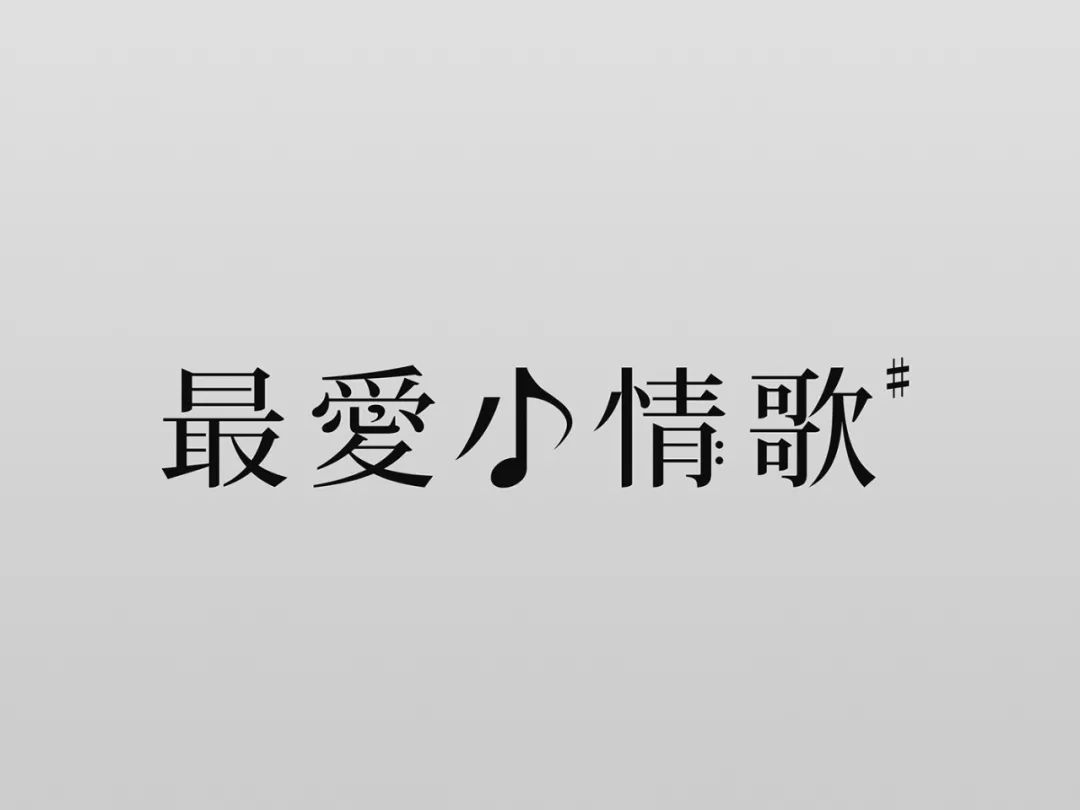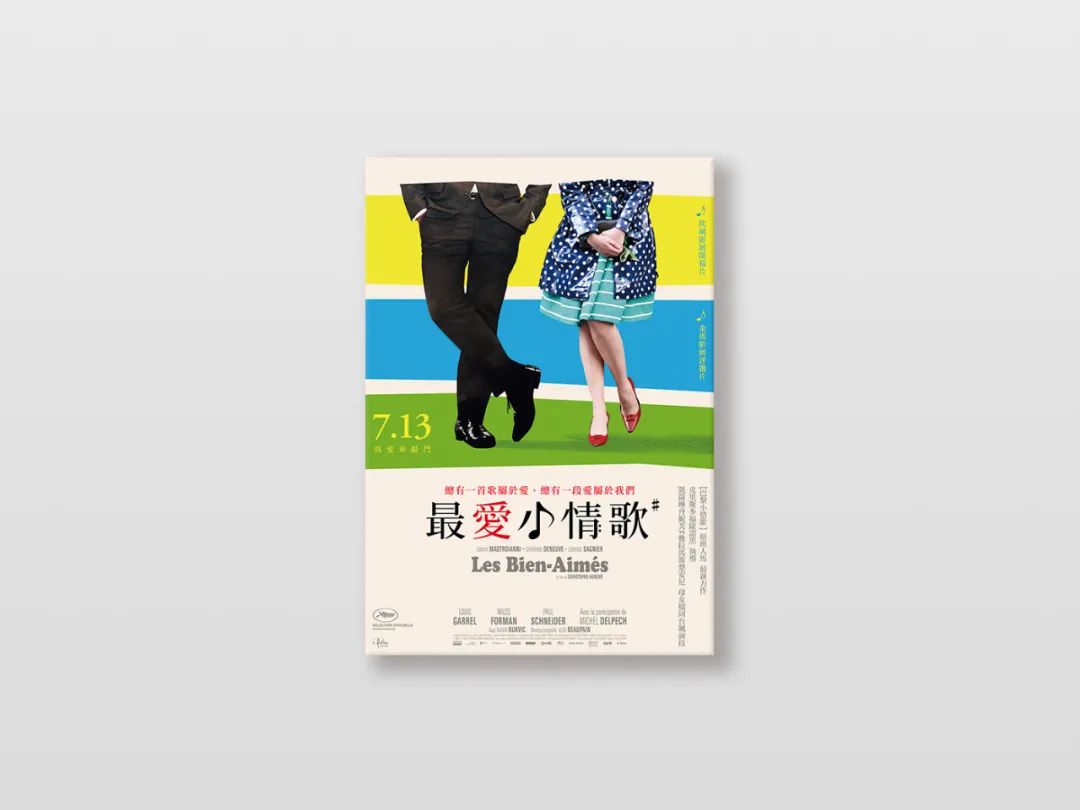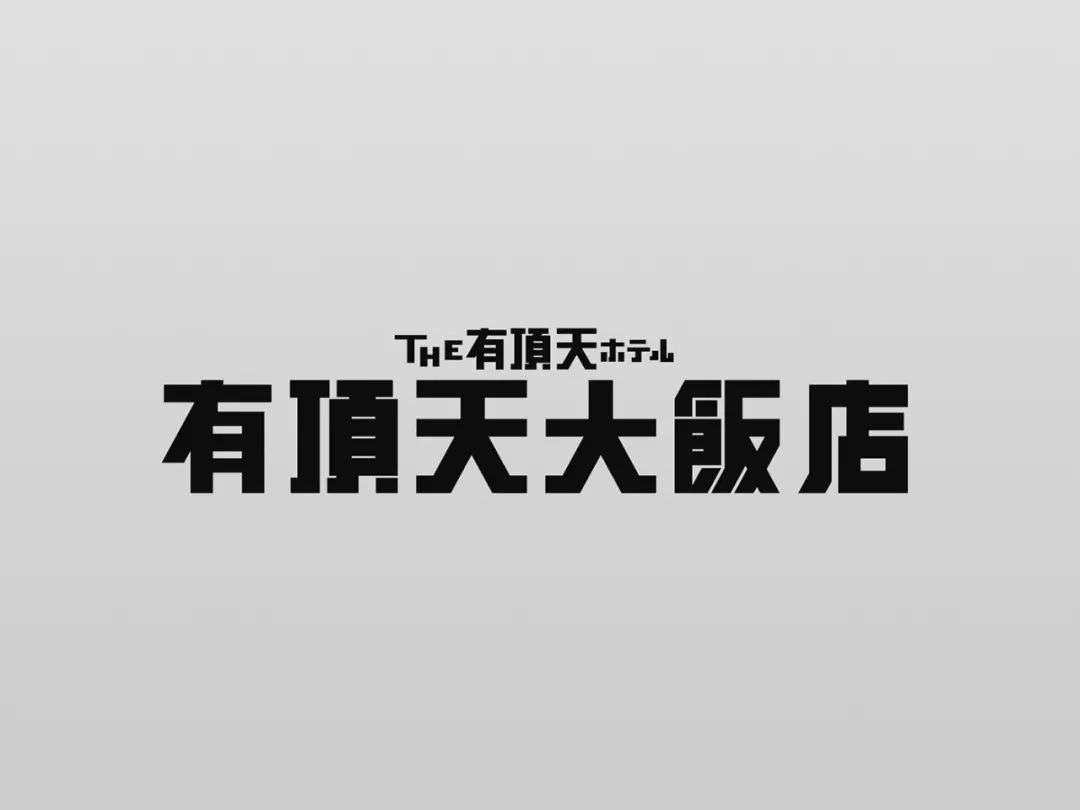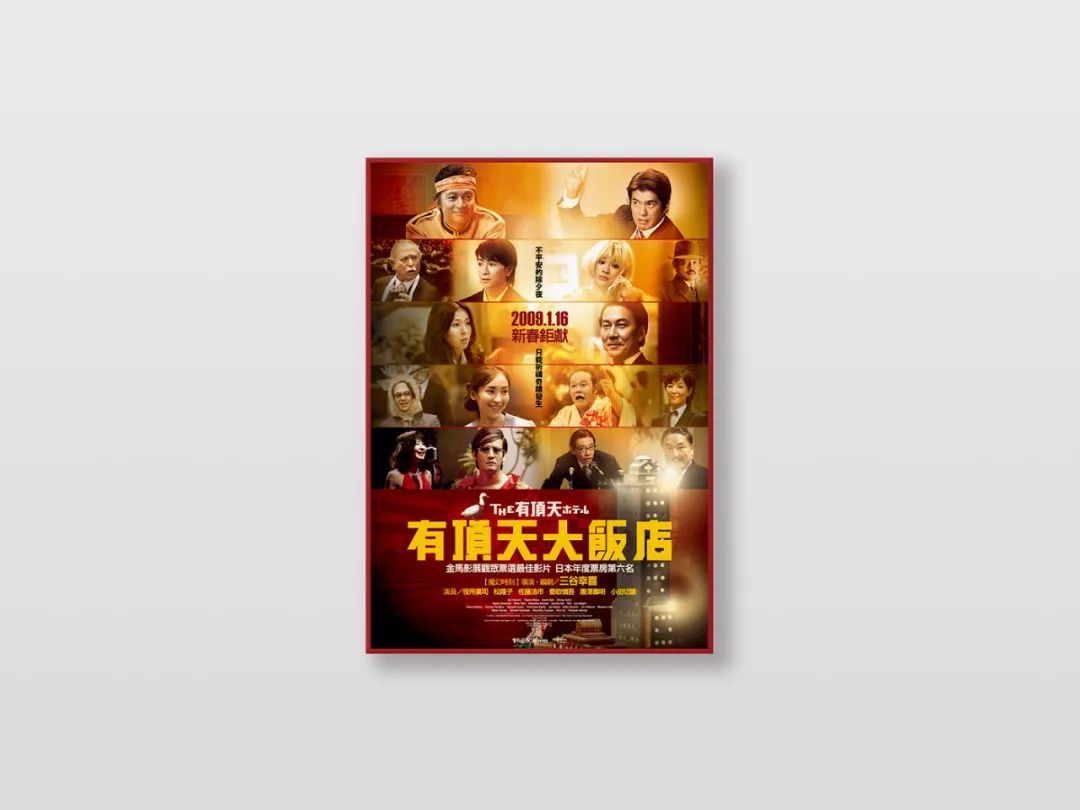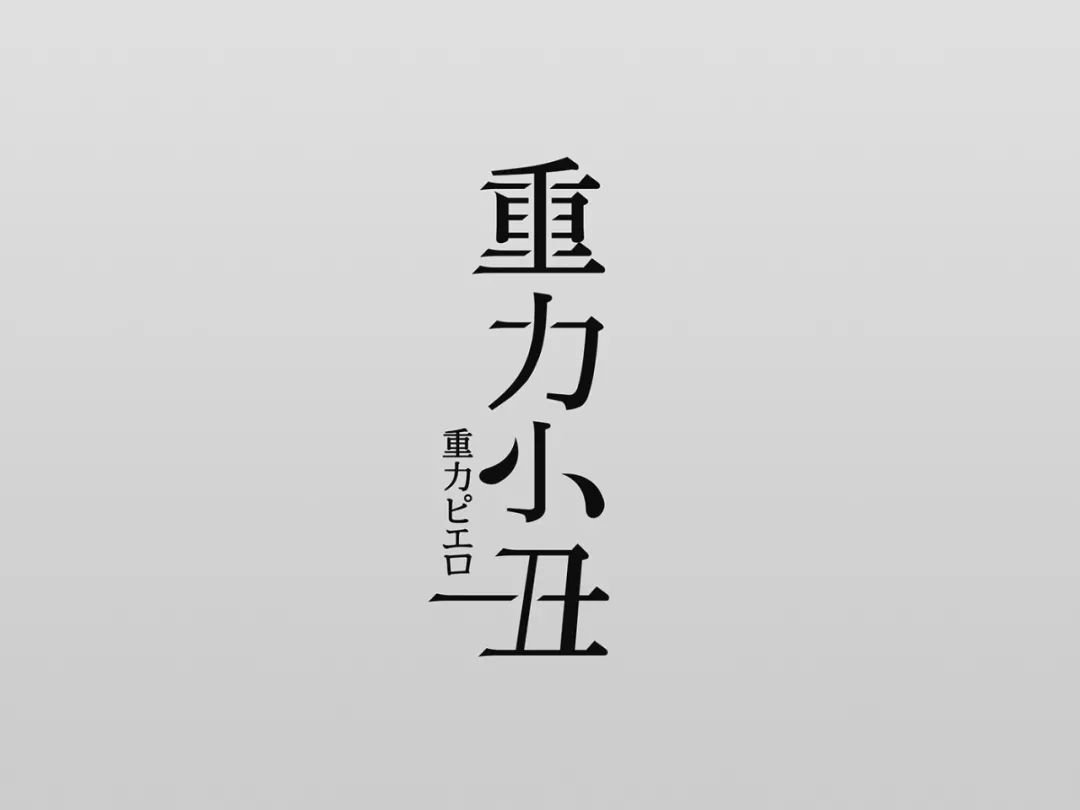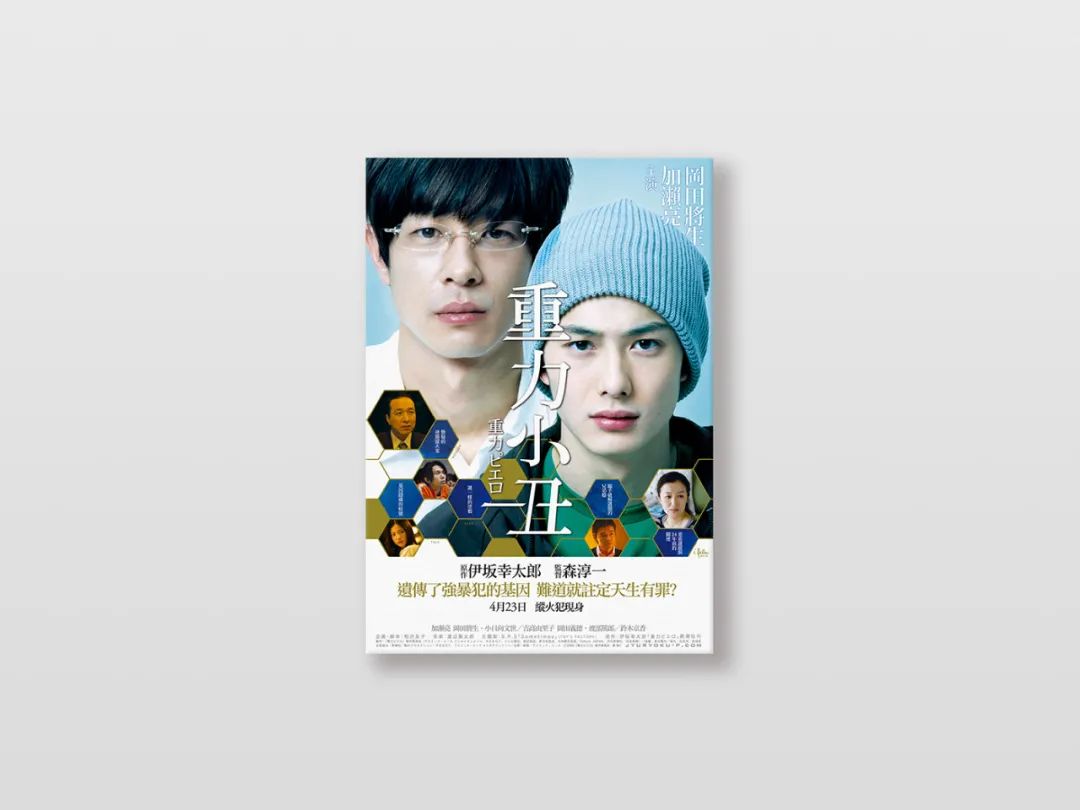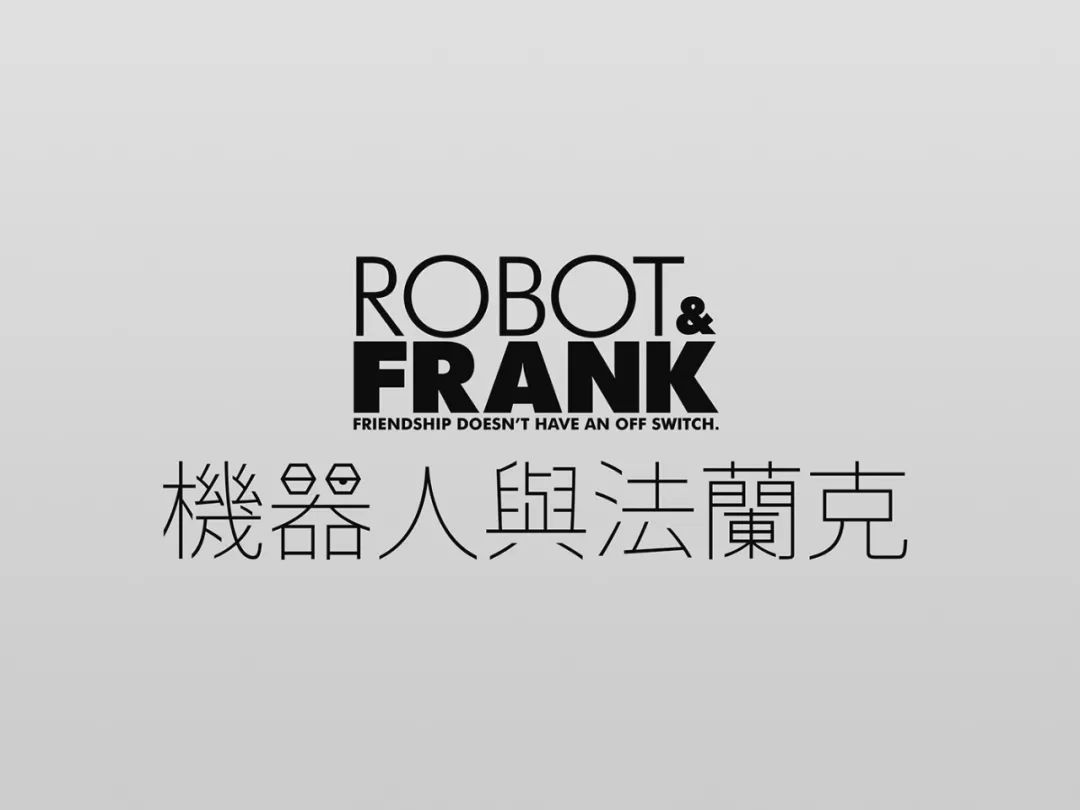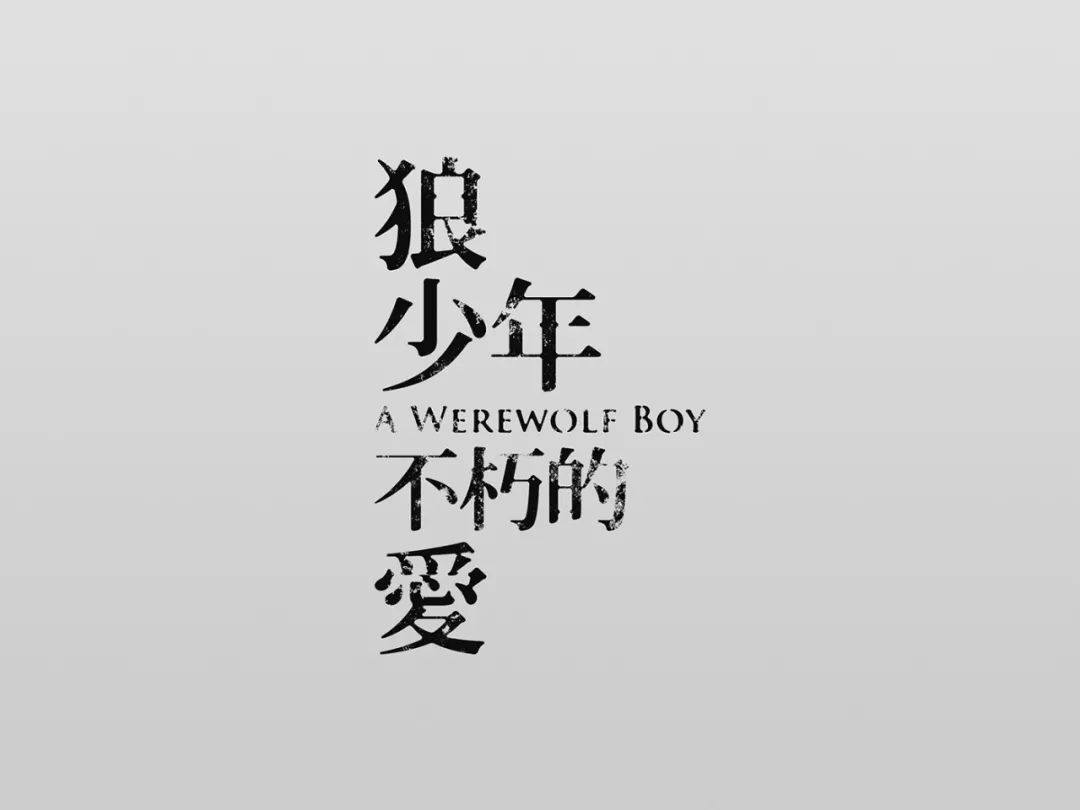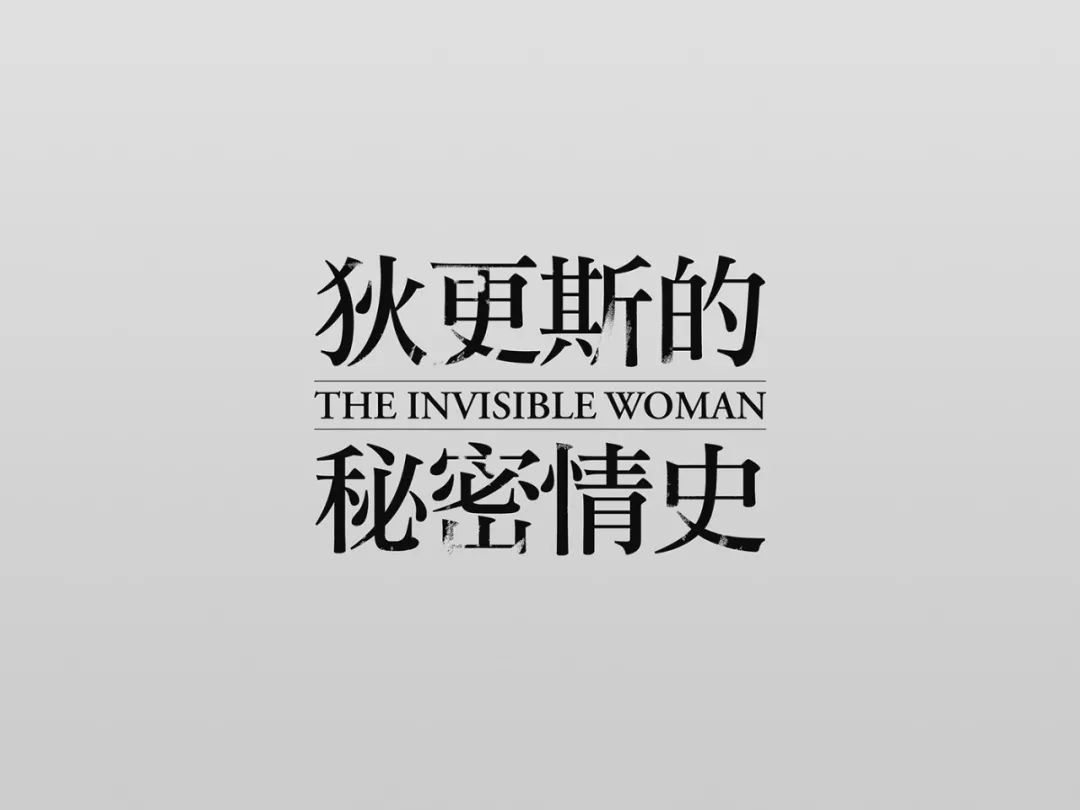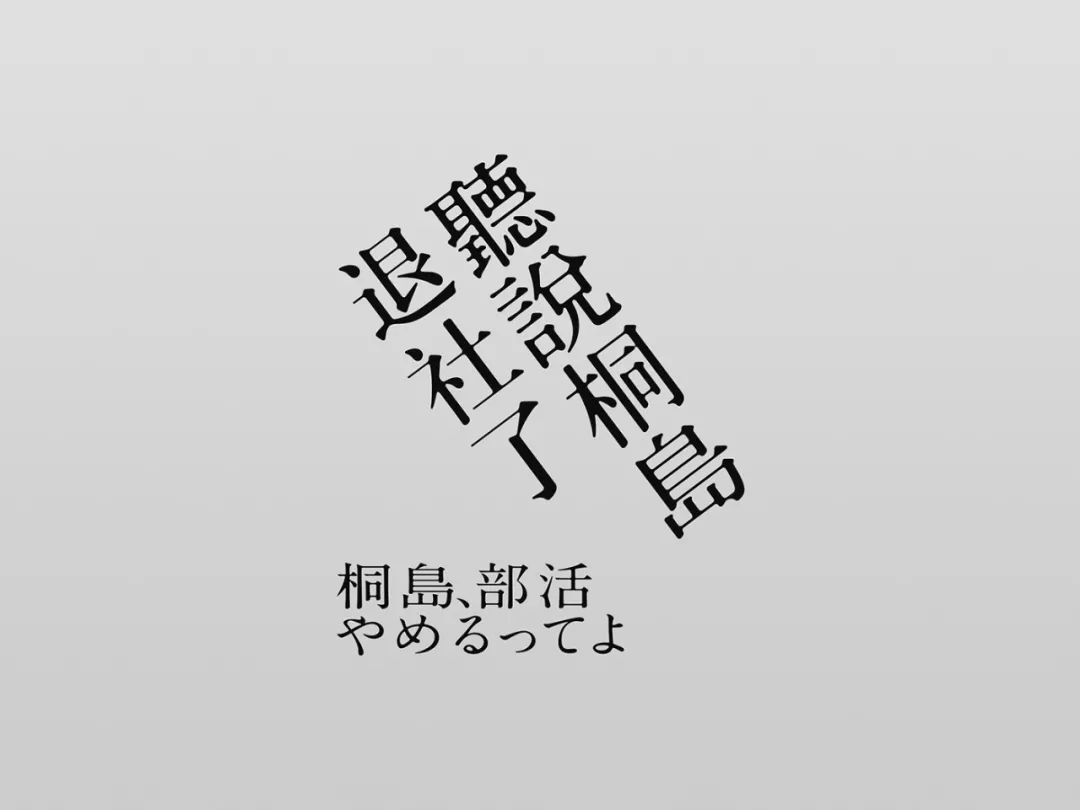
字体设计——10年前的电影片名
朱陈毅,一九八一年生于台北,
二零零六年毕业于崑山科技大学视觉传达设计研究所。
曾任职于诚品书店,目前为自由接案设计师。
今天和大家看看其十年前的电影片名字体设计。
电影片名必须简练概括影片内容、揭示影片主题。而片名的字体选用、造型变幻、肌理表现等设计技巧也极为重要。
要做到电影片名令人过目不忘,除了给电影取个响亮的好名字外,剩下的便是在字体的选用、造型的变幻、肌理的表现等多方面的设计技巧了。
电影片名的字体设计如同其他视觉作品的字体设计一样,应遵照一定的原则才能做到传神达意、雅俗共赏。希望今天的分享对大家有所帮助。